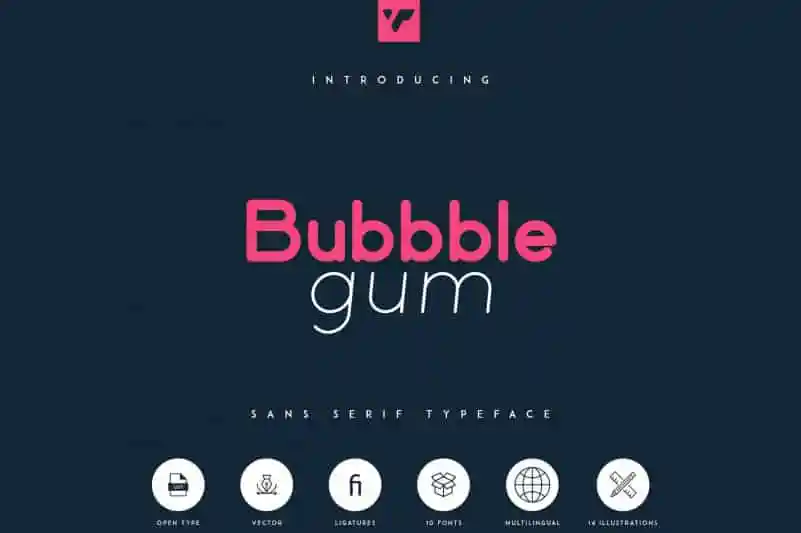
Bubbble Gum Sans Serif Typeface
A Bubbble Gum Sans Serif é uma tipografia moderna e redonda que oferece 10 tipos diferentes – incluindo regular e itálico – para aprimorar sua experiência de design gráfico. Com suporte multilíngue, este conjunto versátil de fonts se destaca tanto em grandes como pequenas proporções. Perfeito para incorporar um toque descontraído e jovial em suas criações digitais, seja ela uma tagline para um site ou a fonte principal de um livro digital, a Bubbble Gum Sans Serif está aqui para entregar um visual único e agradável que cativa os olhos dos leitores. Ideal tanto para designers como para os amantes da boa design, este conjunto de fonts garante uma experiência imersiva e atraente sem deixar o estilo moderno de lado.